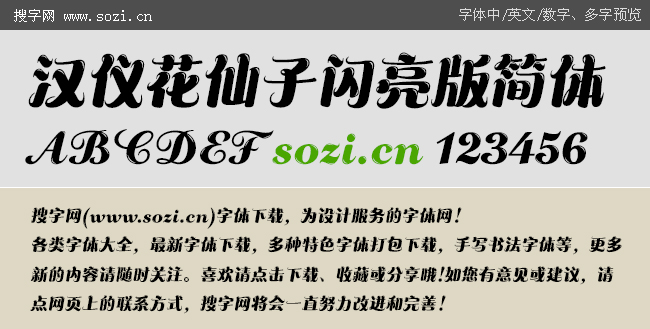
汉仪花仙子闪亮版简体
搜字网给大家提供一款汉仪花仙子闪亮版简体中文字体下载,汉仪花仙子闪亮版简体字体从西文点尖书法中获取灵感,西文书写的优美曲线与汉字书写的规整造型碰撞,生长出了一款极繁主义的中文花体字。字形饱满而圆润,以流动曲线构成的笔画似植物花卉的曼妙姿态,连笔设计与装饰游丝点缀其间,唯美浪漫的氛围随之绽放。适用于画册设计、海报设计、包装设计等场合使用。(本字体为个人非商用版,如需要商用请联系汉仪公司购买版权)